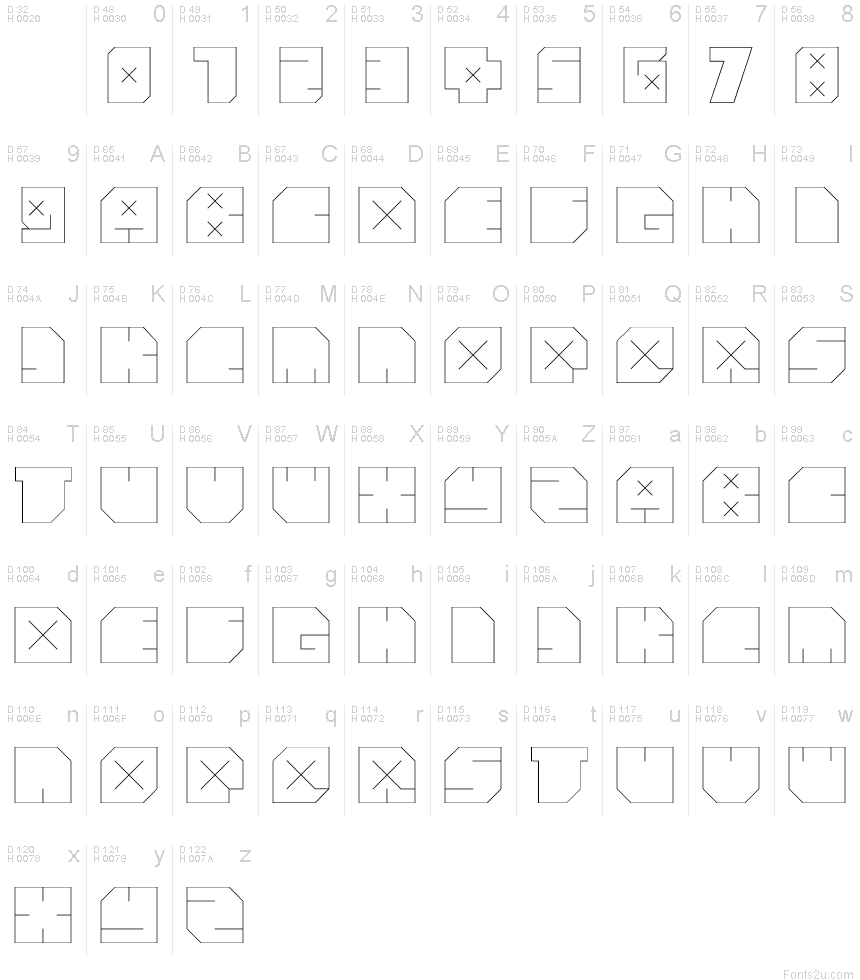
Andrefist 是一款免费的空心科技风标题字体。其字母设计如同极简的科幻标识:开放的几何框架、裁剪的边角以及几处利落的内衬笔画,让每个字形看起来更像是电脑绘制而非手写而成。
这款免费字体非常适合需要酷炫、结构化视觉效果的场景——例如游戏 Logo、电子音乐传单、海报标题、界面风格的品牌设计以及开场字幕。由于其字形极度精简且棱角分明,它在短词、首字母缩写和封面标题中表现最佳,那种断断续续的轮廓节奏感能带来极佳的视觉冲击。